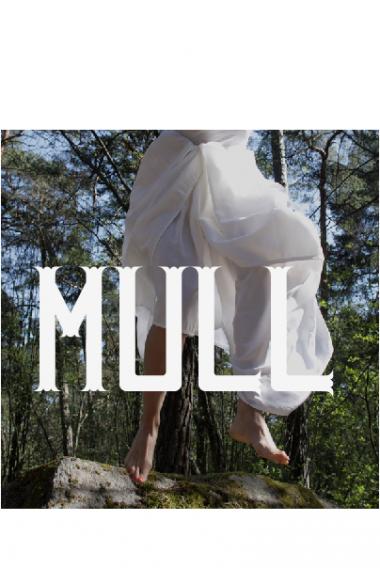
Cisneroles
Úsese para todo tipo de carteles, flyer's, camisetas, etc.
Tienes mi 10 sobre 10 pero bueno, ¿y eso de drogada? Yo la llamaría más bien gótica. Aunque tienes razón. Lo gótico también parece un poco ido.
You got my 10/10 but, why you called it junky? I prefer "gothic". But you're right: Gothic stuff seems a little mad.